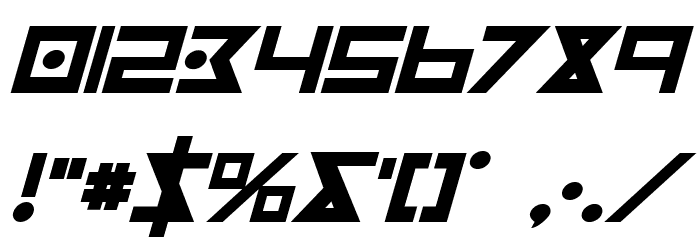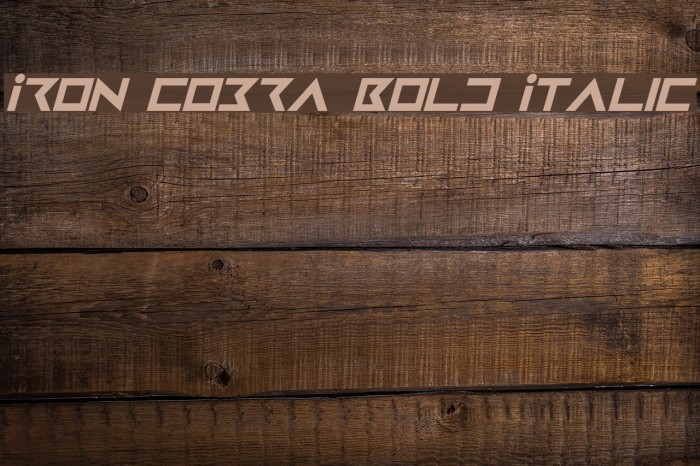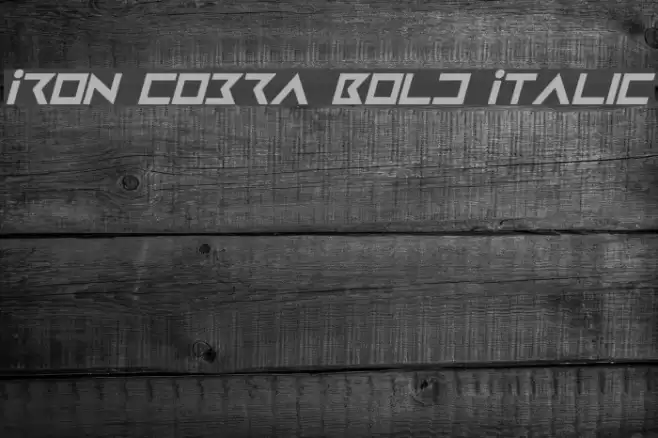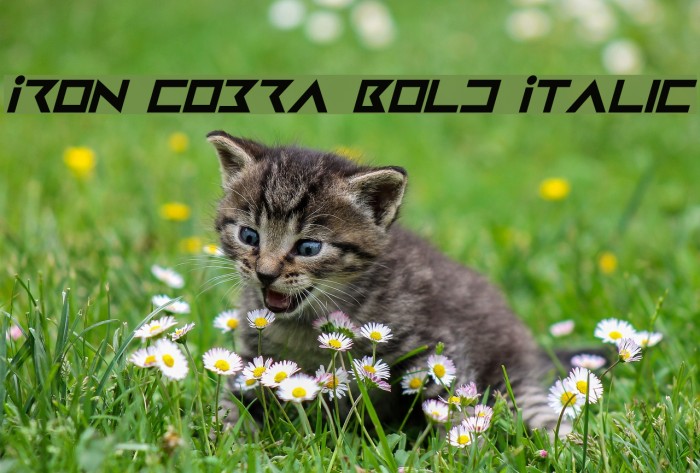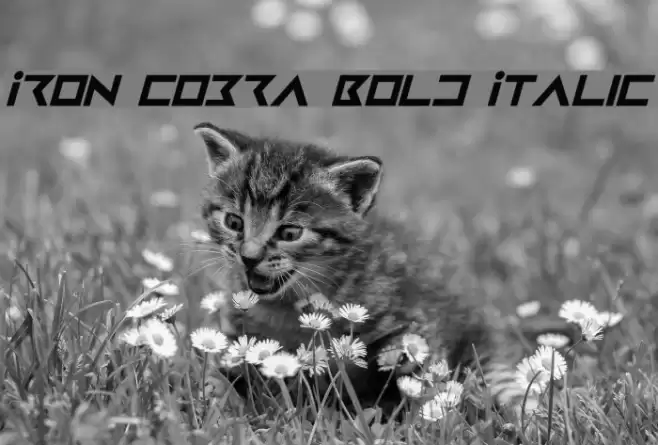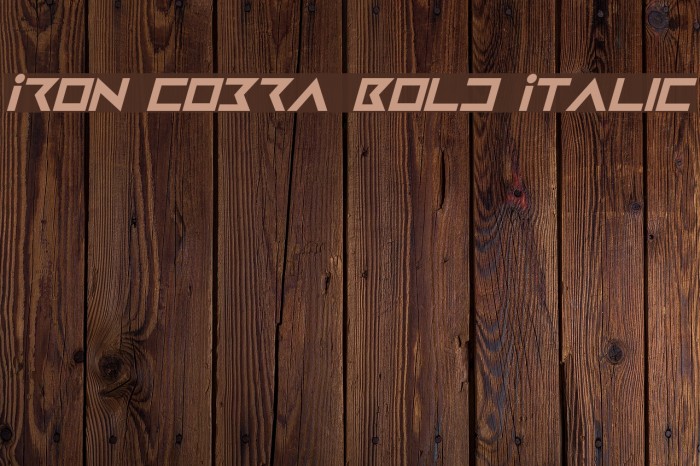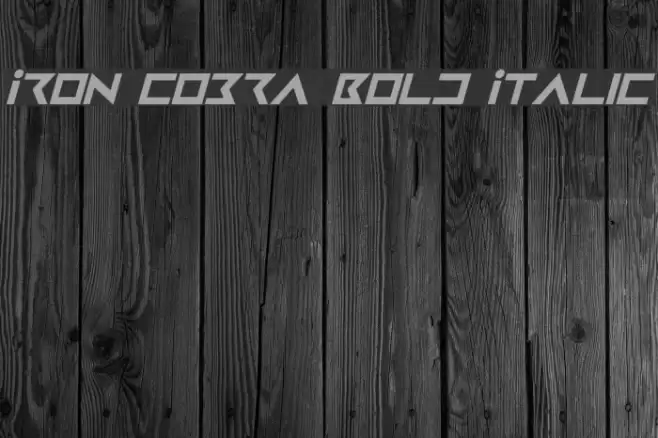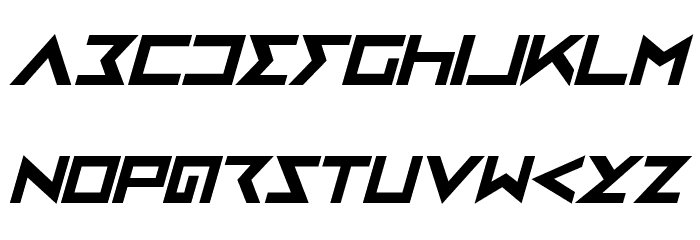
Iron Cobra Bold Italic Font
| Gesamtstil | Futuristic, Modern, Decorative |
| Vorgeschlagene Projekte | Ideal for sci-fi themed projects, video game titles, posters, and branding that requires a modern and edgy look. |